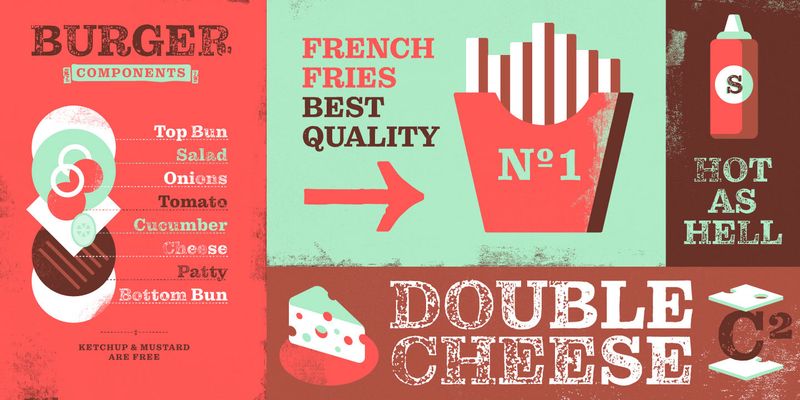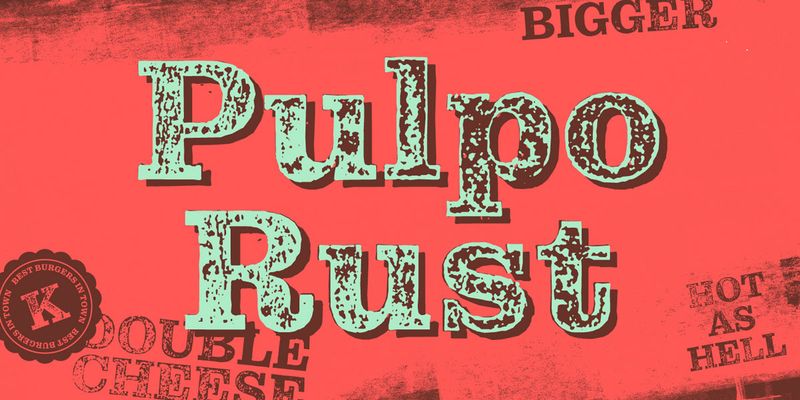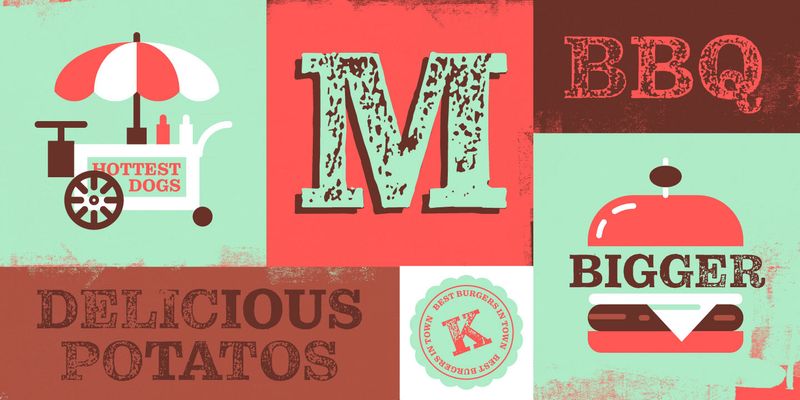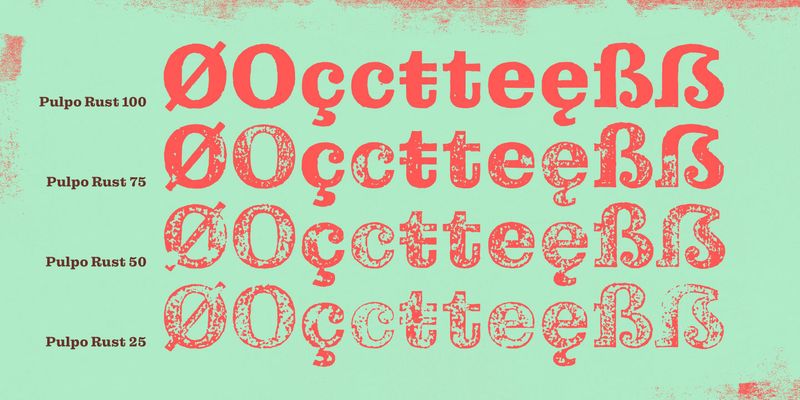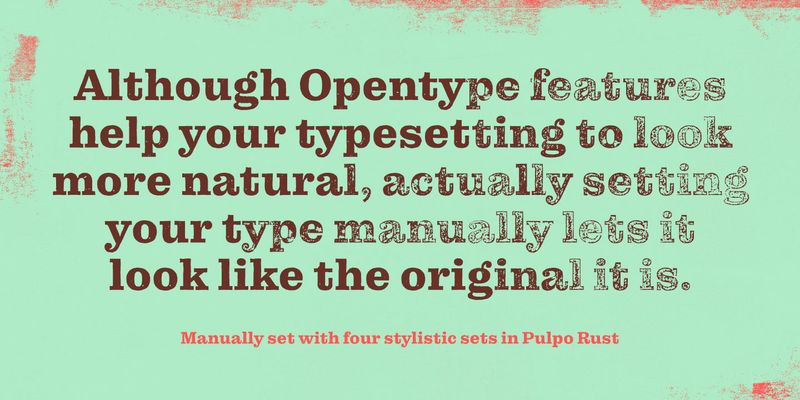
Pulpo Rust представляет собой цифровую имитацию деревянной печати ручной работы. Для каждого из 560 символов шрифта предлагается четыре начертания и дается возможность создавать яркую типографику в соответствии с вашими собственными представлениями. Для создания шрифтов на пяти деревянных пластинах было вручную вырезано 193 глифа, с помощью которых затем делали оттиски. Из бесчисленных тестовых отпечатков четыре самых удачных были оцифрованы и превратились в разные стили.